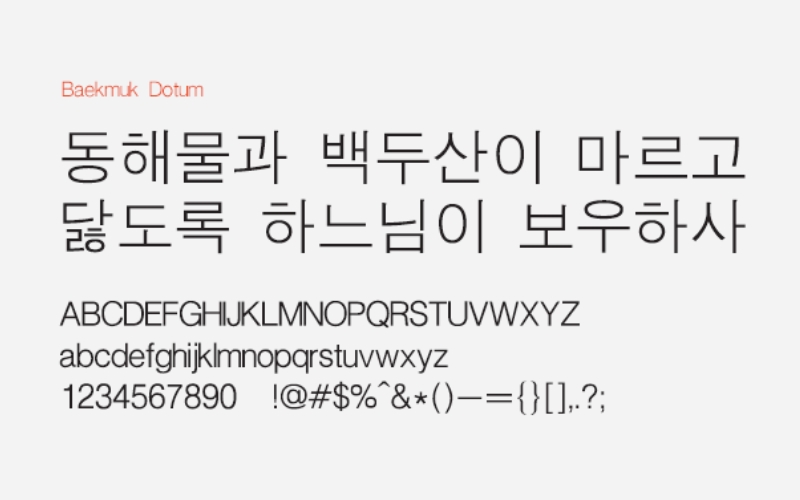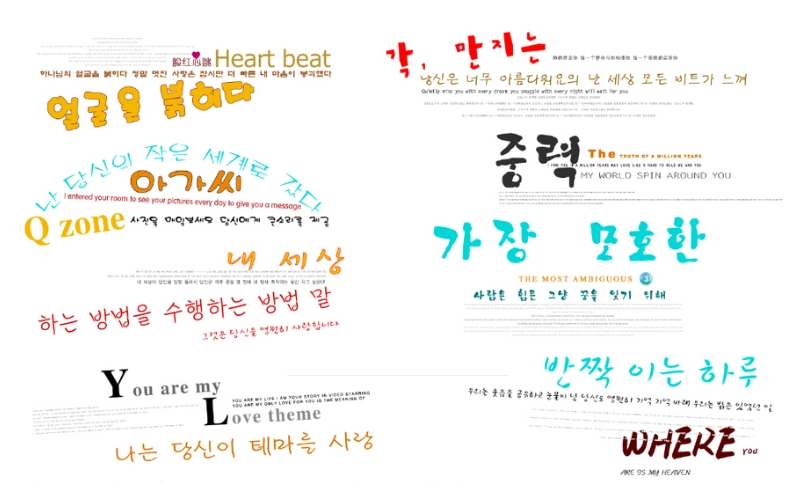
Font tiếng Hàn là gì?
Font chữ tiếng Hàn là loại font được thiết kế để người dùng có thể gõ và hiển thị toàn bộ các ký tự trong bảng chữ cái Hangul, bao gồm tất cả các âm trong tiếng Hàn. Nhiều người khi nhìn thấy chữ Hàn thường lầm tưởng đây là chữ tượng hình, nhưng thực chất Hangul là chữ biểu âm, tức mỗi ký hiệu đại diện cho một âm vị cụ thể.
Tại Việt Nam, font chữ Hàn Quốc được ứng dụng phổ biến trong học tập, giao tiếp và công việc, đặc biệt là ở các công ty Hàn Quốc. Chính vì vậy, nhu cầu tải font tiếng Hàn ngày càng được nhiều người quan tâm và sử dụng rộng rãi.
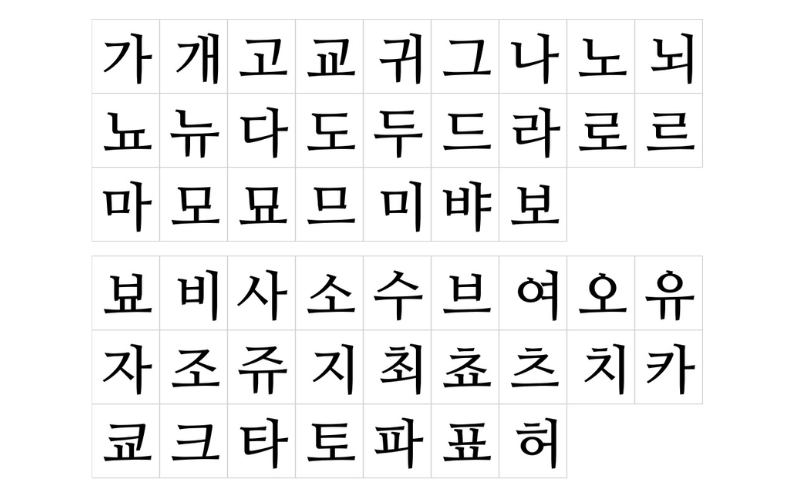
Đặc điểm nổi bật của bộ font chữ Hàn Quốc
Bộ font chữ tiếng Hàn được thiết kế đa dạng về phong cách, giúp người dùng dễ dàng lựa chọn theo nhu cầu trình bày văn bản, từ những tài liệu trang trọng cho đến các thiết kế trẻ trung, sáng tạo. Các font chữ Hàn Quốc hiện nay đều tương thích với hầu hết các hệ điều hành phổ biến như Windows, MacOS hay Linux, đảm bảo khả năng sử dụng linh hoạt trên nhiều thiết bị khác nhau.
Một số đặc điểm nổi bật của font chữ tiếng Hàn gồm:
- Đa dạng phong cách: Bao gồm các kiểu chữ trang nhã, nghiêm túc hoặc năng động, phá cách, phù hợp với nhiều mục đích sử dụng.
- Tính thẩm mỹ cao: Các chữ cái trong font được thiết kế đồng bộ về phong cách, tạo cảm giác hài hòa và thống nhất.
- Ứng dụng linh hoạt: Font chữ có thể sử dụng trên nhiều chất liệu khác nhau như màn hình điện tử, giấy in, decal hoặc các sản phẩm thiết kế.
- Phổ biến và dễ dùng: Bộ font cung cấp các kiểu chữ thông dụng, thích hợp cho nhiều hoạt động từ học tập, làm việc đến sáng tạo nội dung.
Việc tải font chữ tiếng Hàn giúp người dùng dễ dàng áp dụng ngay lập tức vào các dự án thiết kế hoặc văn bản học tập, làm việc mà không cần lo lắng về khả năng tương thích hay thẩm mỹ.
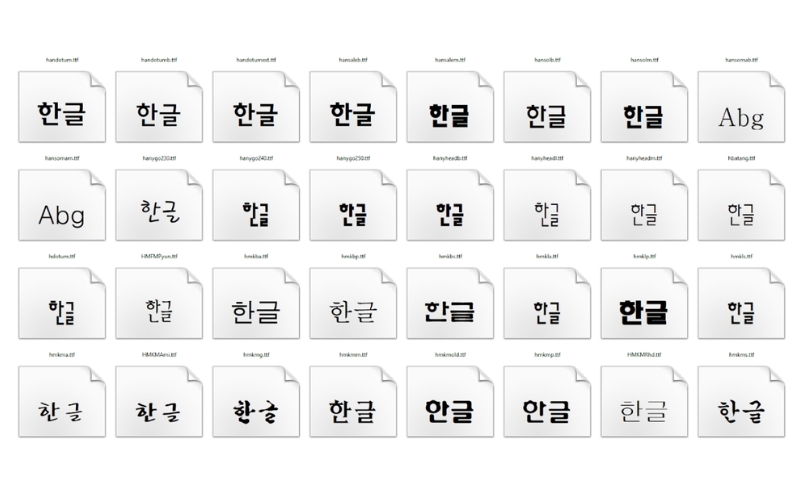
Các font chữ tiếng Hàn đẹp và thông dụng hiện nay
Việc lựa chọn font chữ phù hợp sẽ giúp văn bản hay thiết kế trở nên ấn tượng và chuyên nghiệp hơn. Hiện nay, có rất nhiều font chữ Hàn Quốc đẹp và phổ biến, đáp ứng nhu cầu học tập, làm việc và sáng tạo nội dung. Dưới đây là những lựa chọn được nhiều người ưa chuộng khi tải font tiếng Hàn để sử dụng trên máy tính và các thiết bị khác:
Font Gugi
Gugi là một font chữ tiếng Hàn được thiết kế với các đường nét bo tròn mềm mại ở các cạnh, mang lại cảm giác thân thiện và dễ nhìn. Một số ký tự trong font còn được thêm các dấu chấm trang trí, tạo điểm nhấn thú vị cho văn bản. Ngoài việc hiển thị đầy đủ các chữ cái Hangul, font Gugi còn hỗ trợ chữ Latin với cả chữ hoa, chữ thường, các con số và nhiều ký tự đặc biệt, giúp người dùng linh hoạt trong nhiều mục đích sử dụng khác nhau.
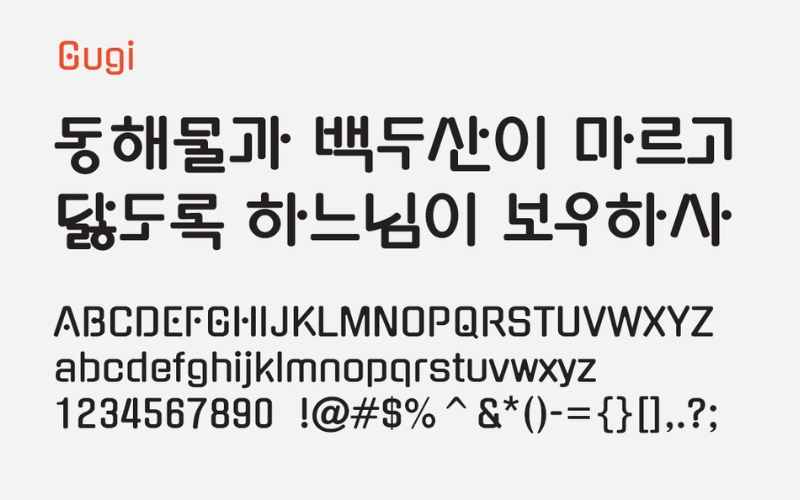
Font Noto Serif
Noto Serif là một font chữ tiếng Hàn được thiết kế theo phong cách Serif, do Google phát triển và duy trì, giúp người dùng dễ dàng áp dụng trên các nền tảng của Google. Đặc trưng của font là các đầu và cuối nét được thiết kế thanh mảnh, tạo cảm giác nhẹ nhàng, tinh tế cho từng ký tự. Font Noto Serif phù hợp để sử dụng trong nhiều mục đích khác nhau, từ văn bản học tập, tài liệu chuyên nghiệp đến thiết kế sáng tạo.
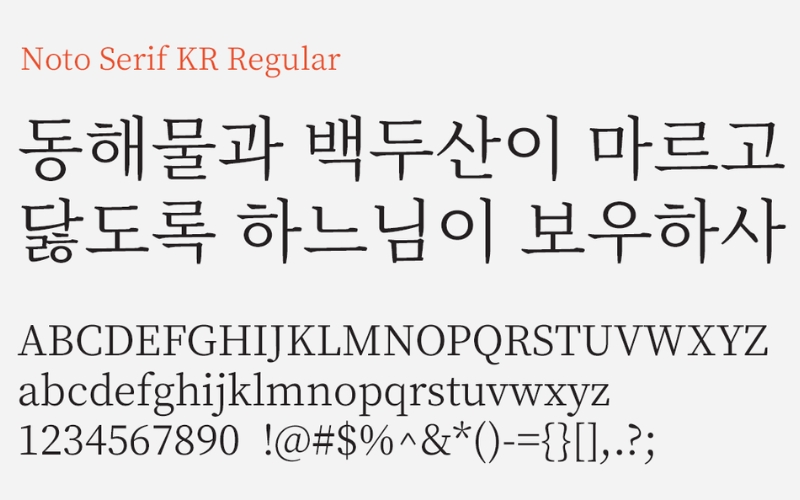
Font Nanum Gothic
Nanum Gothic là một font chữ Hàn Quốc được phát triển và phát hành bởi Naver (Sandoll), đồng thời là font chính được cổng thông tin lớn nhất Hàn Quốc – Naver – sử dụng. Các ký tự trong bảng chữ cái Hangul của font được thiết kế với các đường nét bo tròn, thanh mảnh, mang đến cảm giác tinh tế và thân thiện khi đọc. Khi cài font tiếng Hàn Nanum Gothic, người dùng có thể dễ dàng áp dụng cho nhiều mục đích khác nhau, từ soạn thảo văn bản, thiết kế đồ họa đến trình bày nội dung trên web.
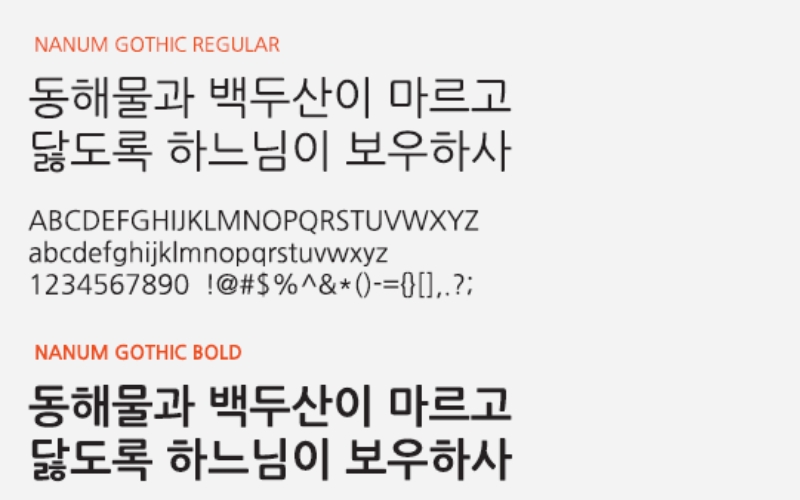
Font Nanum Myeongjo
Nanum Myeongjo là một font thuộc bộ Nanum, được phát triển và phát hành bởi Naver (Sandoll, Fontrix). Font chữ này được thiết kế theo phong cách Myeongjo hiện đại, mang nét thanh lịch và trang nhã, phù hợp cho nhiều loại văn bản khác nhau. Khi tải font tiếng Hàn Nanum Myeongjo, người dùng có thể dễ dàng áp dụng vào soạn thảo tài liệu, thiết kế ấn phẩm hoặc các dự án sáng tạo, mang đến sự chuyên nghiệp và thẩm mỹ cao.
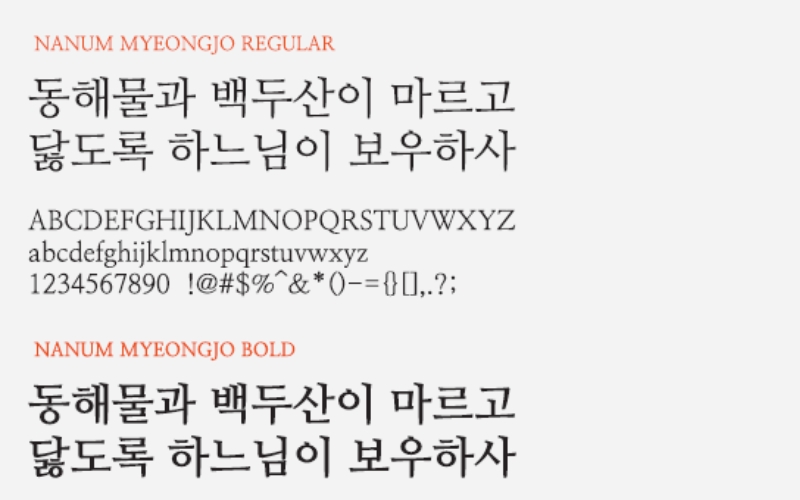
Font Gowun Batang
Gowun Batang là một font thuộc bộ Gowun, được thiết kế bởi nữ nhà thiết kế Yanghee Ryu. Mỗi nét chữ trong font được chăm chút tỉ mỉ, mang đến cảm giác tinh tế và cân đối. Đặc biệt, hai đầu của mỗi nét được làm dày hơn một chút, giúp các ký tự trở nên rõ ràng và dễ đọc hơn. Font Gowun Batang phù hợp để sử dụng trong nhiều loại văn bản và dự án thiết kế, mang đến sự trang nhã và chuyên nghiệp cho nội dung hiển thị.